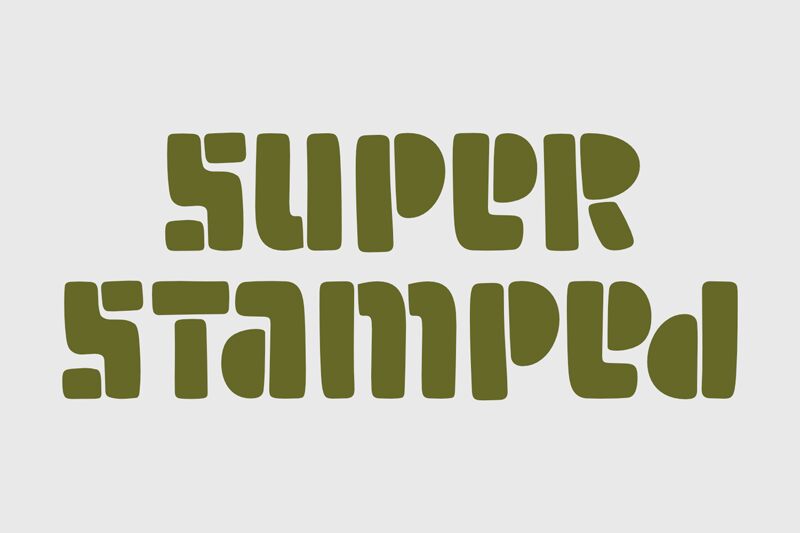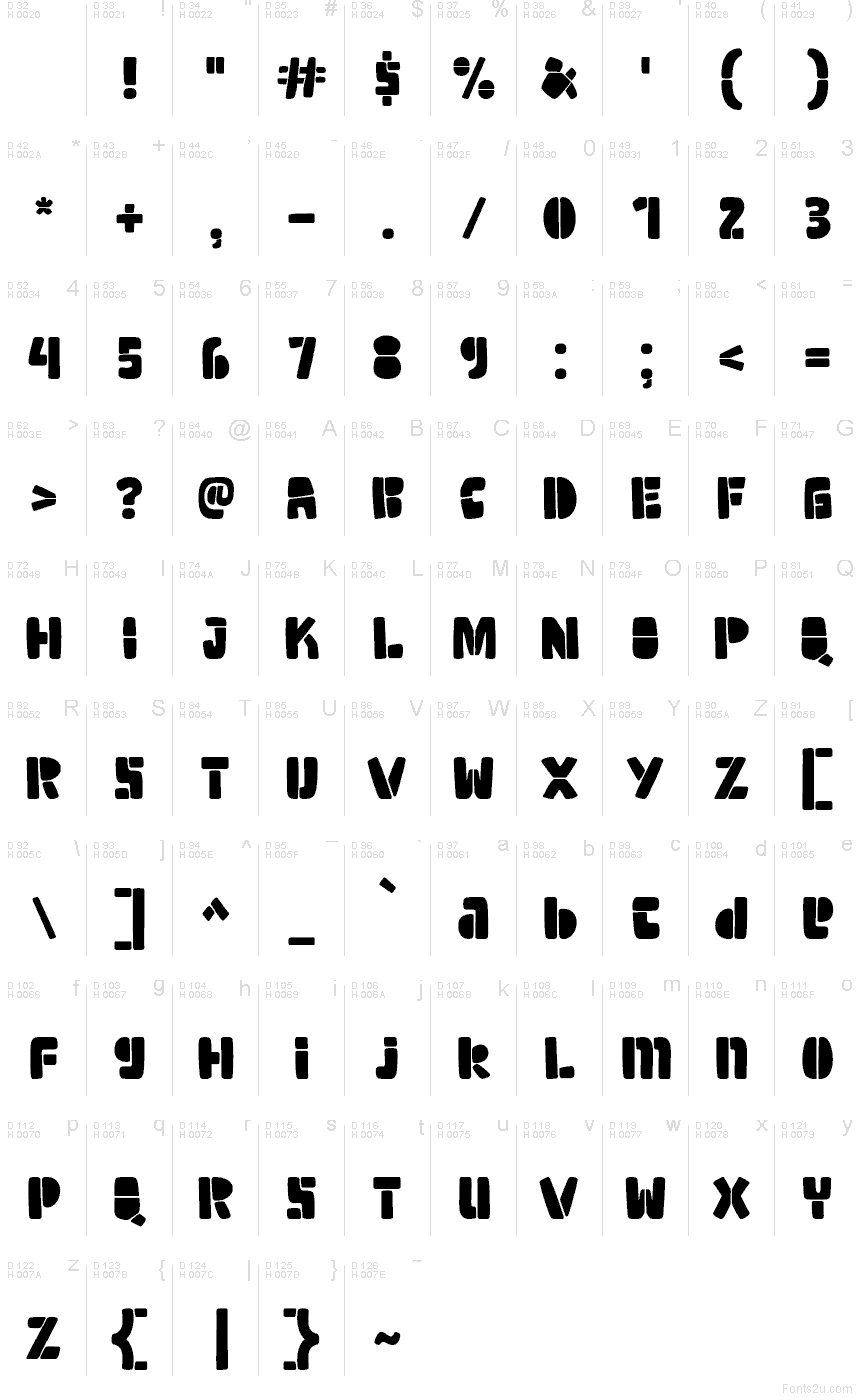
Super Stamped Regular
Super Stamped to darmowy, ciężki krój typu display sans o kanciastych, miękko zaokrąglonych literach i delikatnej nieregularności form drukarskich wyciętych ręcznie. Jego szerokie kształty sprawiają, że litery wydają się masywne i zwarte.
Plakaty to jego najsilniejsze środowisko, szczególnie w przypadku wydarzeń lub kampanii poszukujących bezpośredniego uderzenia napisów szablonowych bez ścisłej militarnej geometrii. Te same stemplowane formy pasują do wytrzymałych opakowań, gadżetów i grafiki gier, gdzie mogą sugerować sprzęt przemysłowy, skrzynie z zaopatrzeniem, etykiety warsztatowe lub komiksową grafikę akcji.